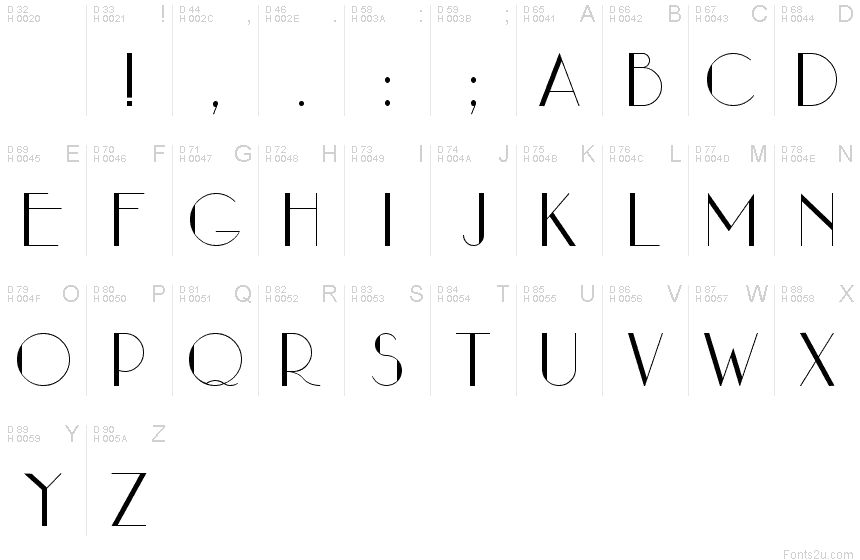
Arwen od Keystrokes to darmowy, retro krój typu display, który przecina przestrzeń dzięki swoim ostrym jak brzytwa przekątnym i niezwykle cienkim liniom. Wysokie, eleganckie litery wyciągają się z gracją modelki na wybiegu, a subtelne krzywizny sprawiają, że kształty liter nie sprawiają wrażenia zimnych czy mechanicznych. Rodzina Arwen emanuje stylem high-fashion – przywodzi na myśl błyszczące magazyny, jasne światła studia i czysty, biały papier.
Dzięki Arwen Regular tytuły stają się natychmiast luksusowe i wyrafinowane, nawet przy użyciu zaledwie kilku znaków. Ten darmowy font doskonale sprawdzi się w brandingu modowym, opakowaniach perfum i kosmetyków, nagłówkach redakcyjnych, plakatach, zaproszeniach na wydarzenia oraz w logotypach wymagających kunsztownego, couture’owego charakteru. W tekstach głównych Arwen warto połączyć z prostym, geometrycznym bezszeryfowym krojem, aby jego dramatyczne, rzeźbiarskie formy pozostały w centrum uwagi.